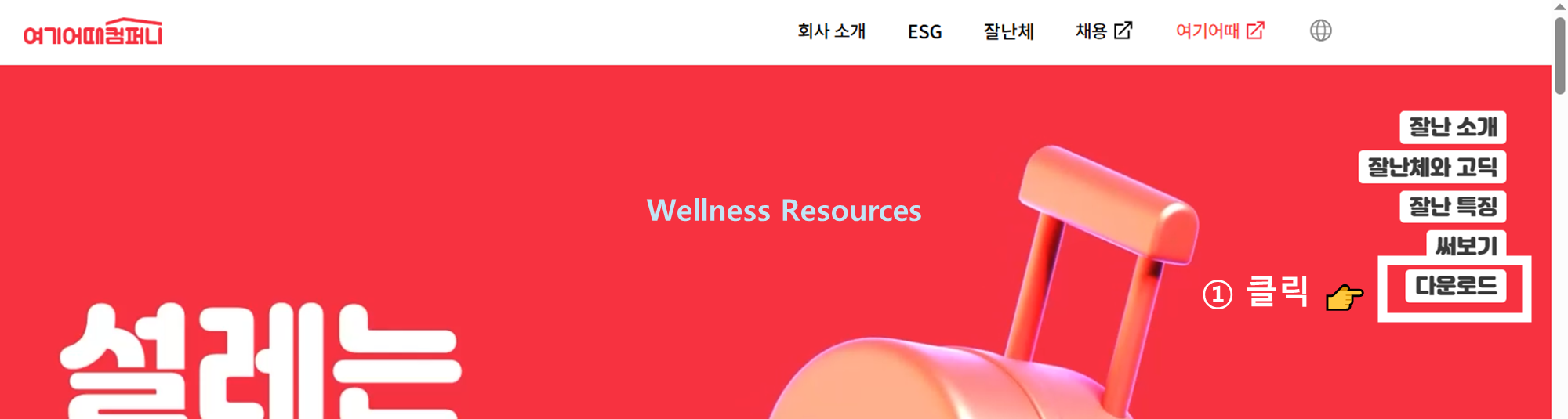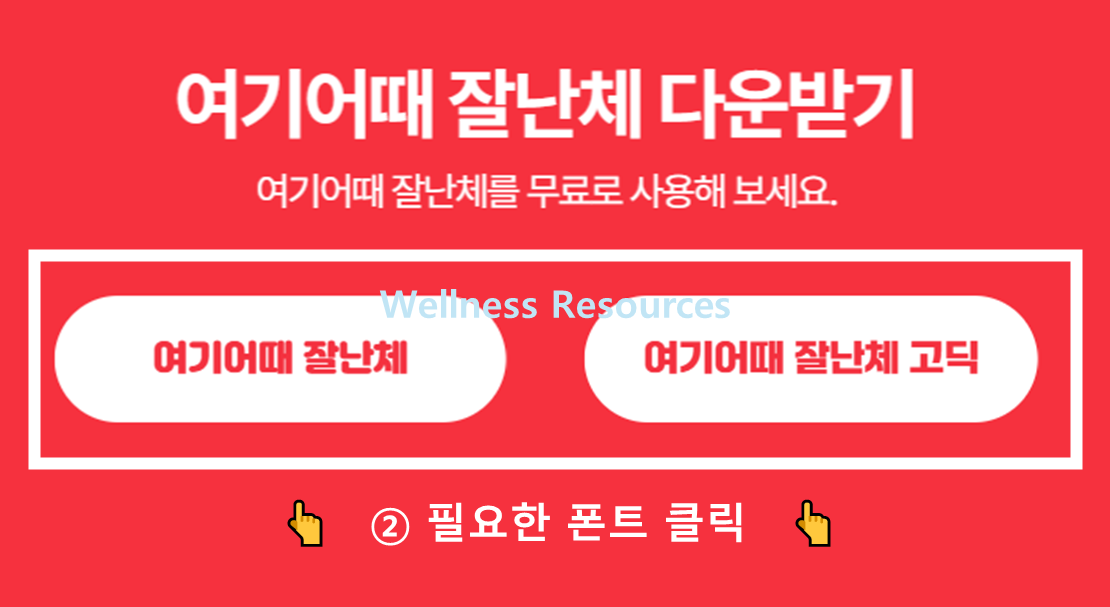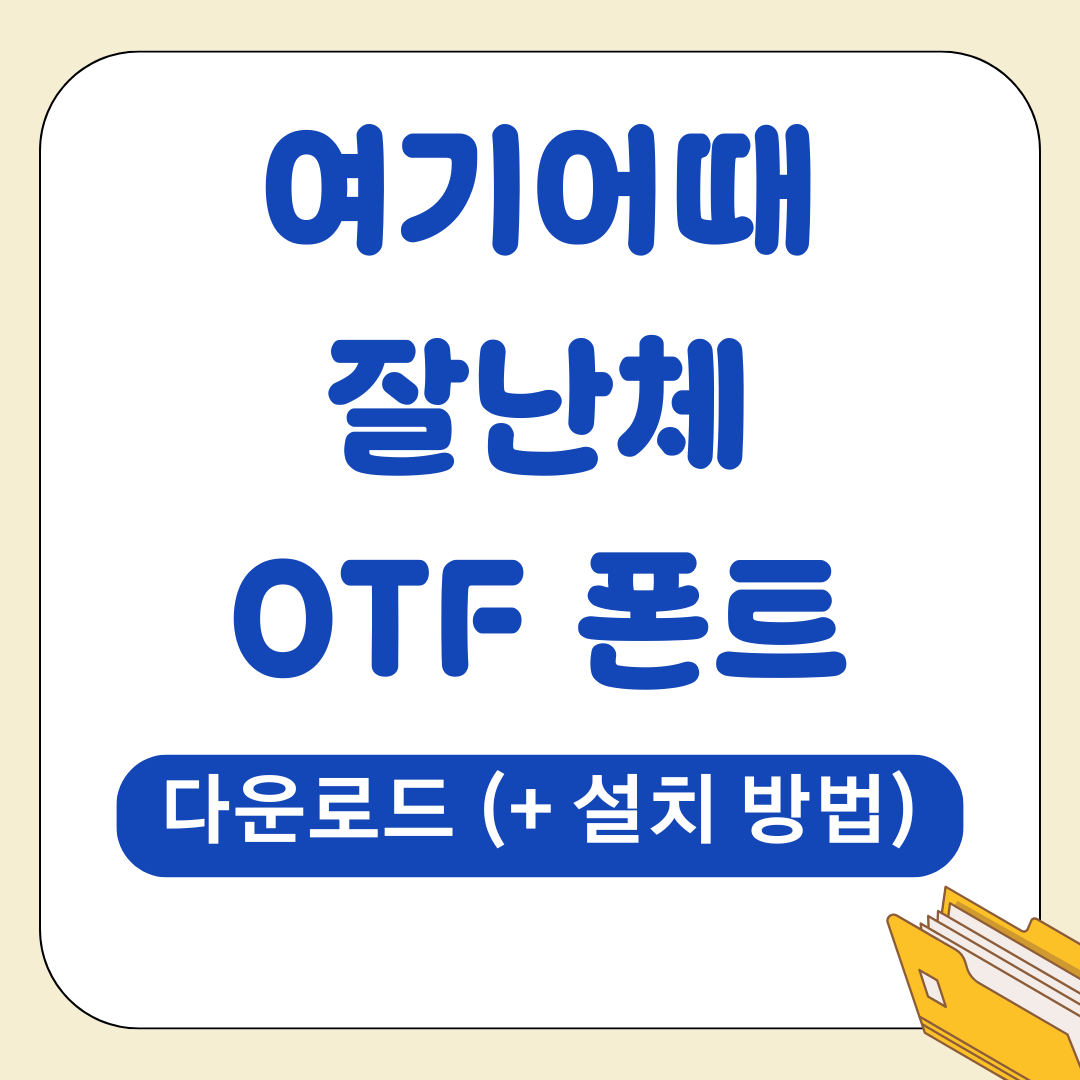
여기어때 잘난체 폰트는 굵고 둥글둥글한 디자인으로 감성적인 매력을 갖춘 무료 글꼴입니다. 윈도우 TTF, Mac OTF 형식으로 간편하게 설치할 수 있으며, 개인과 상업적 프로젝트 모두 활용 가능합니다. 아이콘·포스터·썸네일 등 제작물에 적용하기 좋습니다. 특히 제목에 잘 맞습니다.
| 특징 | 둥근 끝부분, 굵은 선, 가독성 뛰어남 |
| 활용 | 웹사이트, 블로그, 소셜 미디어, 광고, 로고 등 |
여기어때 잘난체는 숙박 플랫폼 여기어때에서 제공하는 공식 무료 글꼴로, 굵고 둥근 디자인이 특징입니다. 감성적이면서도 시각적으로 돋보이는 스타일이라 웹사이트, 디지털 콘텐츠, 광고 등 다양한 프로젝트에서 활용할 수 있습니다.
| 디자인 | 둥근 끝부분과 굵은 선 결합, 가독성 뛰어남 |
| 감성 | 브랜드 감성 강조, 시각적 메시지 전달력 우수 |
| 범용성 | 웹, 블로그, 소셜 미디어, 배너, 로고 등 다양한 활용 가능 |
이 글씨체는 특히 제목이나 강조 텍스트에 활용하면 시각적 효과가 극대화되며, 브랜드의 개성을 전달하는 데 매우 효과적입니다.
- 웹사이트 디자인: 방문자 눈길을 사로잡는 감성적 텍스트
- 블로그 포스팅: 강조 문구, 제목 폰트 활용
- 소셜 미디어 그래픽: 시각적 메시지 강화
- 기업/광고물 제작: 로고, 배너, 마케팅 자료 등
잘난체는 둥근 디자인과 굵은 선 덕분에 시각적 임팩트가 강하며, 다양한 디지털 콘텐츠에 자연스럽게 녹아들 수 있습니다.